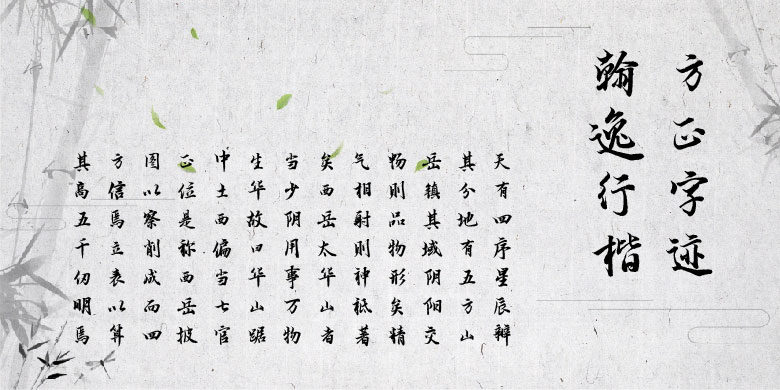
方正字迹-翰逸行楷
方正字迹-翰逸行楷 翰逸行楷结体俊秀,用笔方圆结合,纤丝连带自然,有顾盼神飞之感,笔画入锋时稍显童年锐气,收笔时往往厚重大胆,尤其是横划和点划收笔,稳如磐石,总体书风高矮胖瘦正斜兼备,在变化中求美感,力求灵动而闲澹的表现力,流露出童年的拙朴和锐气。翰谐音韩,逸为神逸,故书体命名为“翰逸行楷”。
该字体适用于现代诗歌、短文的排版,文化类的宣传设计以及商品类品牌的广告和产品包装设计等。